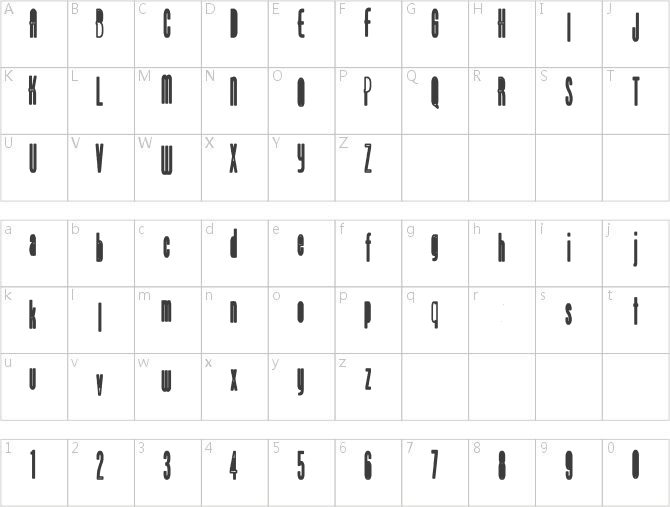
Venus-Normal Hollow Bold
Venus-Normal Hollow Bold介紹
Venus-Normal Hollow Bold字體字庫是一款讓人賞心悅目、百看不厭的英文字體,適合各類廣告和產品包裝設計應用,字體大小0.07MB,格式為ttf字體,上傳用戶是浪遍塞納河的,作者/版權方為未知